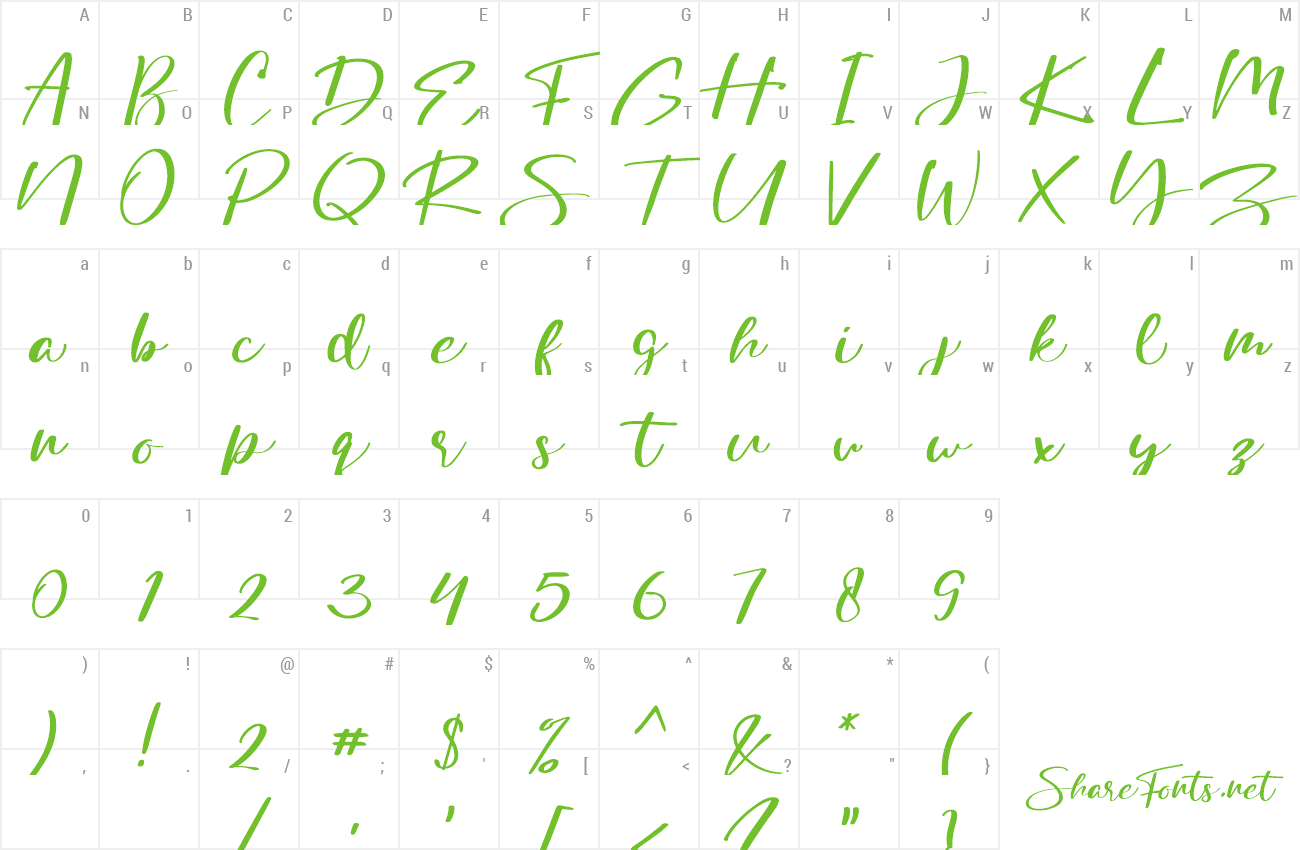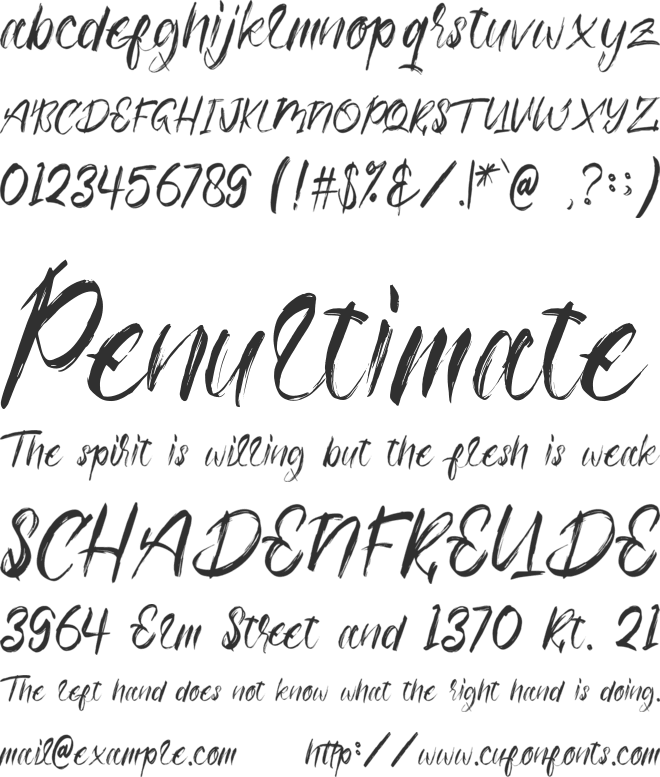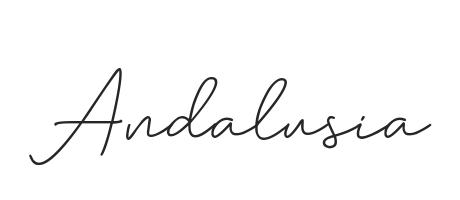
macam macam font script
Macam macam font script. Font yang satu ini memiliki bentuk yang paling menarik terdiri dari berbagai macam karakteristik tipografi dan perpaduan yang klasik dan unik membuatnya disukai oleh desainer grafis. Font script adalah jenis font yang suka digunakan untuk cover ff bertema sad horror dll. Setiap tulisan yang ditampilkan dengan html css akan secara otomatis menggunakan default fonts nya html css yaitu web safe fonts. Jenis font ini juga dikenal dengan nama font display dan font ornamental.